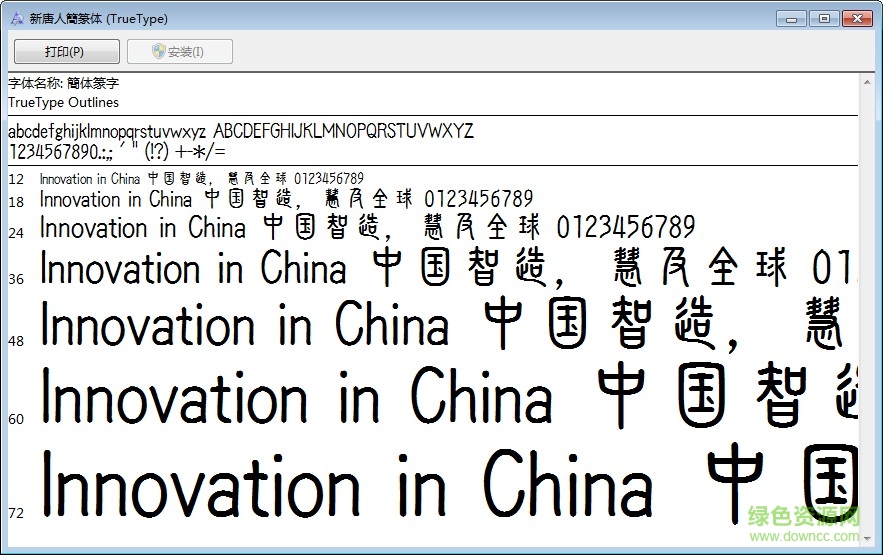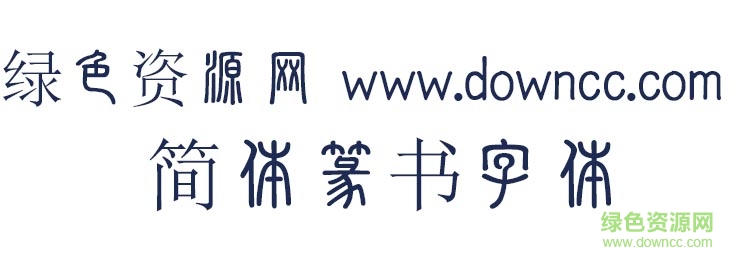
簡(jiǎn)體篆書字體
簡(jiǎn)體篆書字體是一款經(jīng)典的簡(jiǎn)體篆書字體,字形精美文雅,線條簡(jiǎn)練生動(dòng),可應(yīng)用于廣告設(shè)計(jì)、藝術(shù)設(shè)計(jì)等領(lǐng)域,喜歡的朋友歡迎在綠色資源網(wǎng)下載!
簡(jiǎn)體篆書字體
簡(jiǎn)體篆體簡(jiǎn)介:
簡(jiǎn)體篆書字體是一款應(yīng)用于設(shè)計(jì)方面的簡(jiǎn)體篆體字體,字形曲線柔美,非常適合用于各類設(shè)計(jì)當(dāng)中,讓你的主題更鮮明,效果更為明顯。有需要的朋友趕快來綠色資源網(wǎng)下載使用吧!